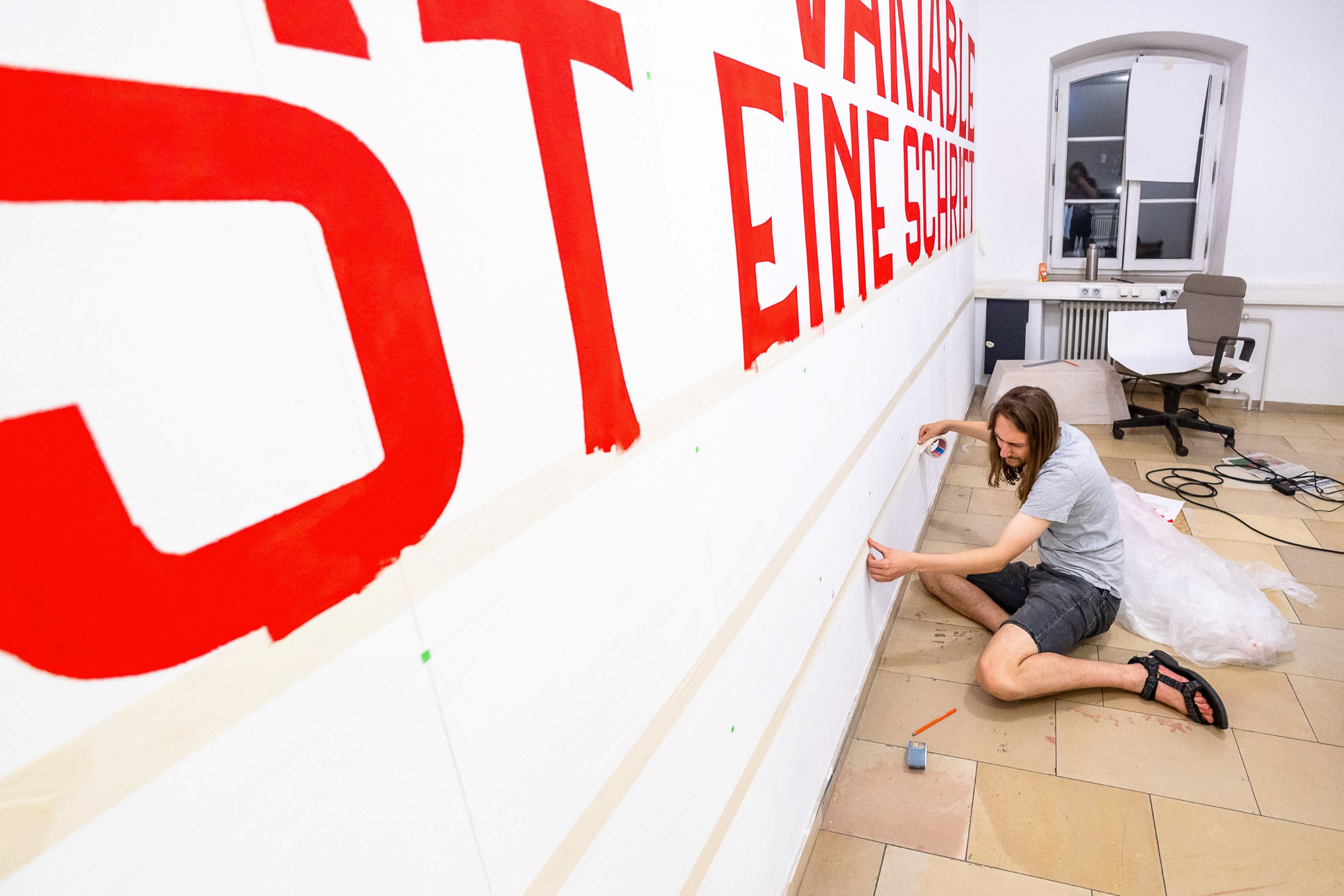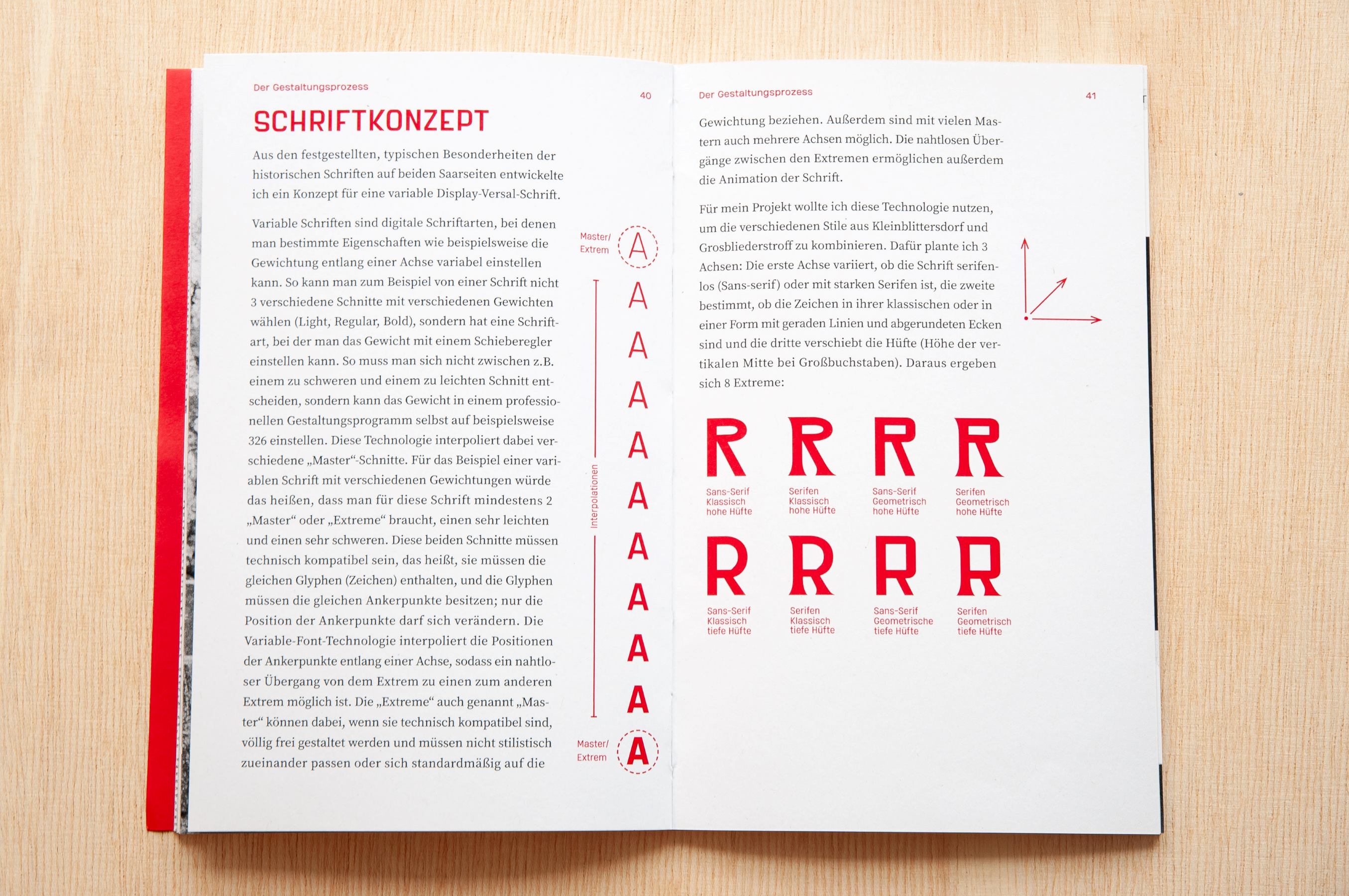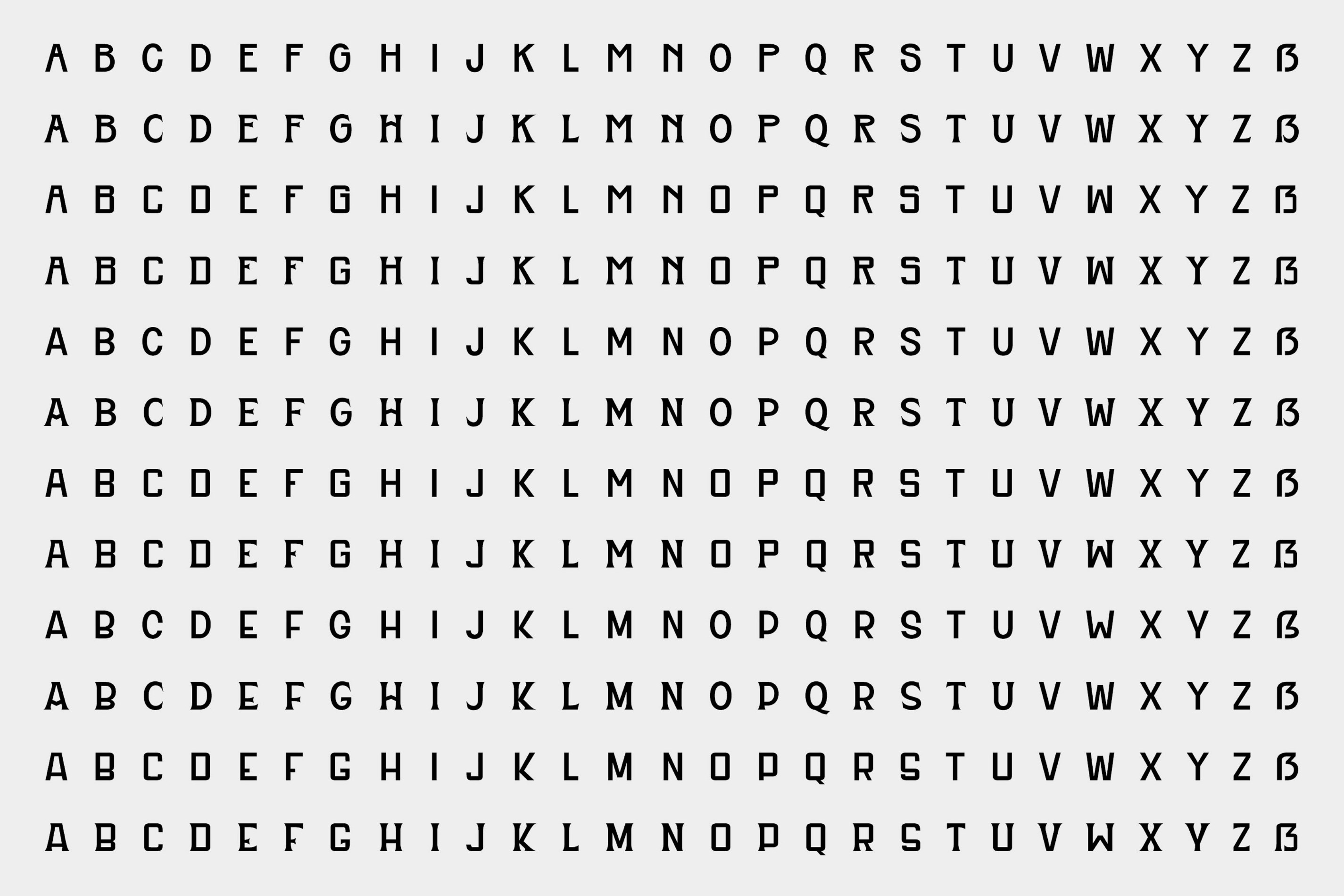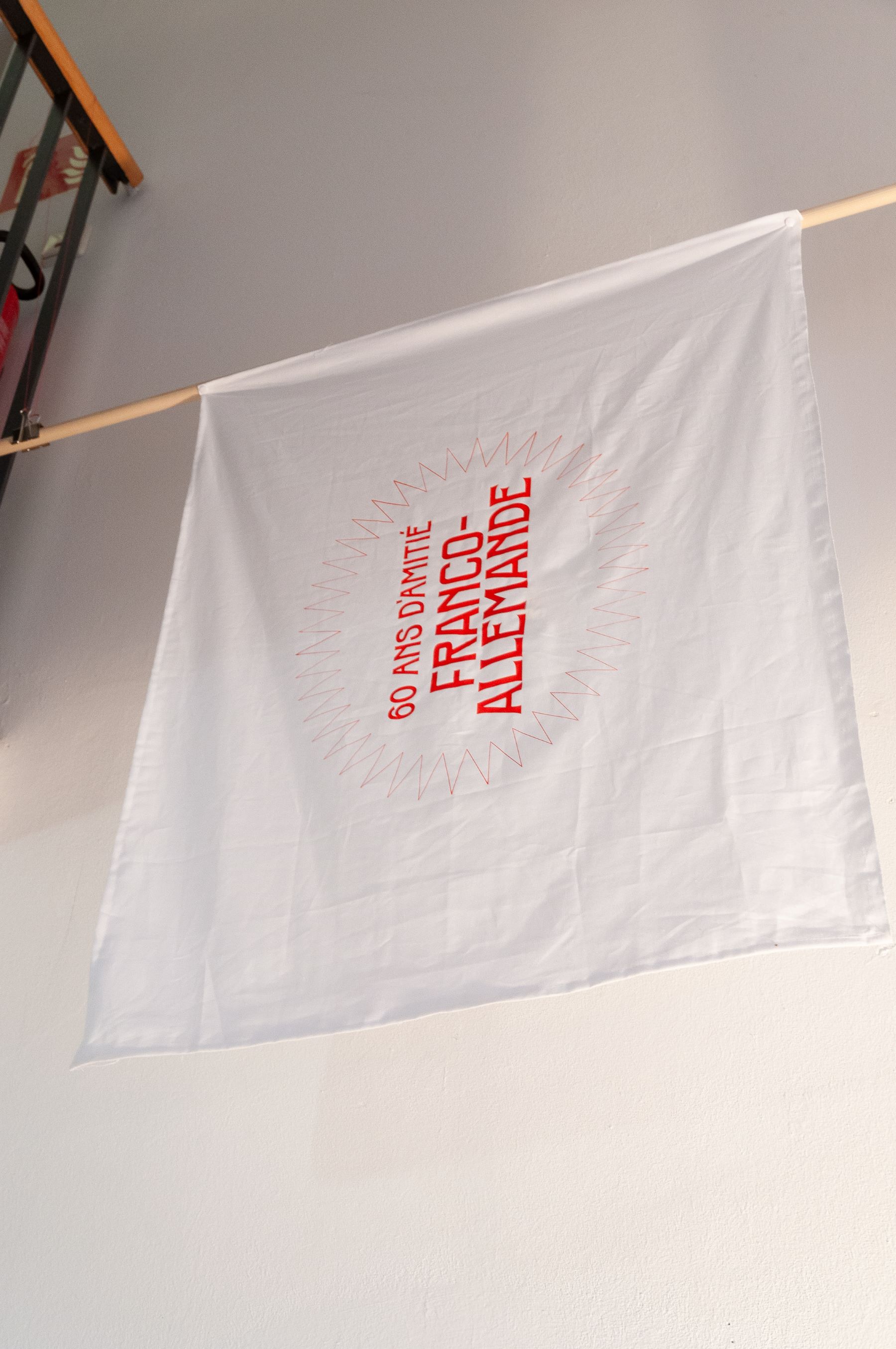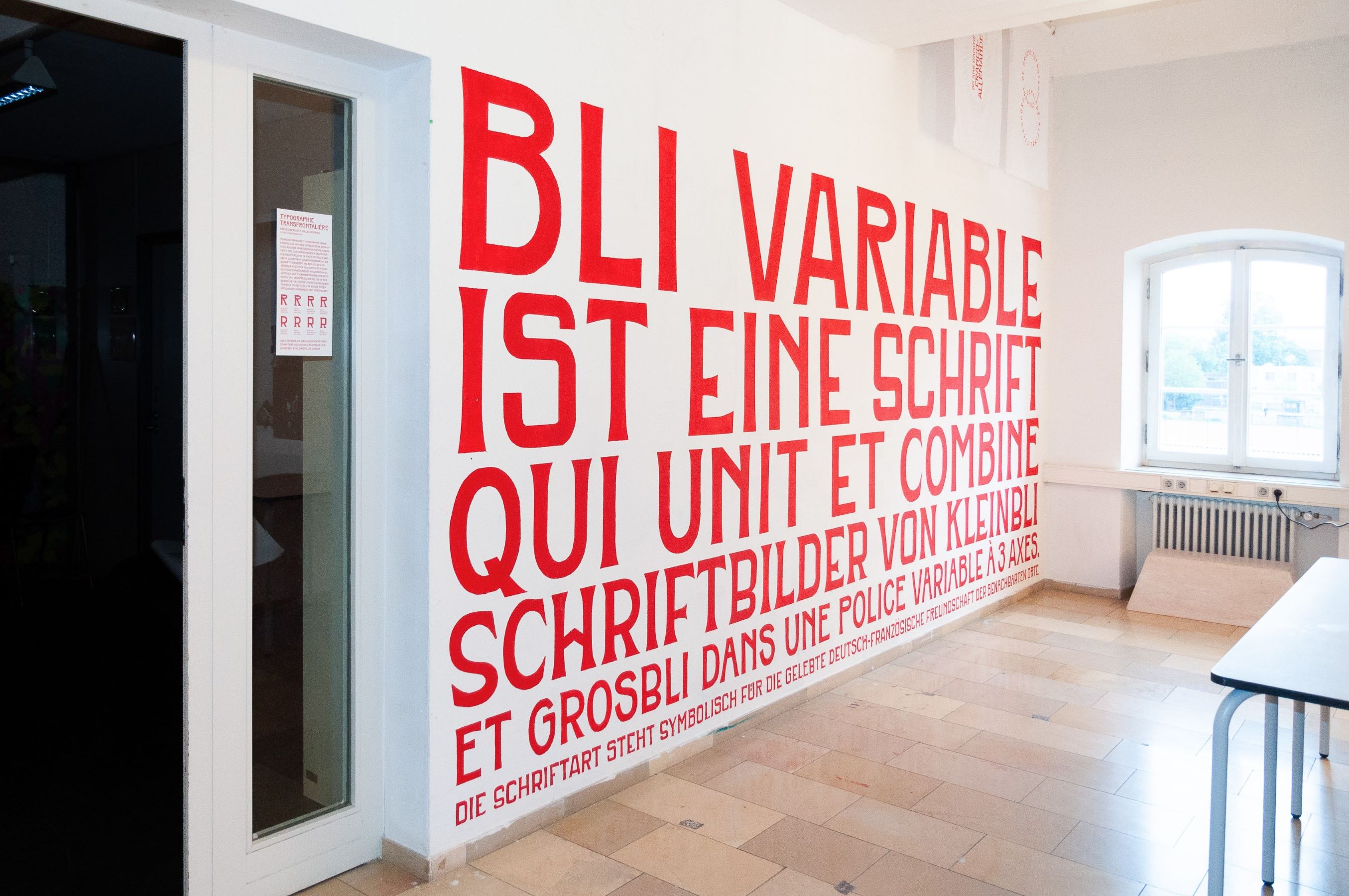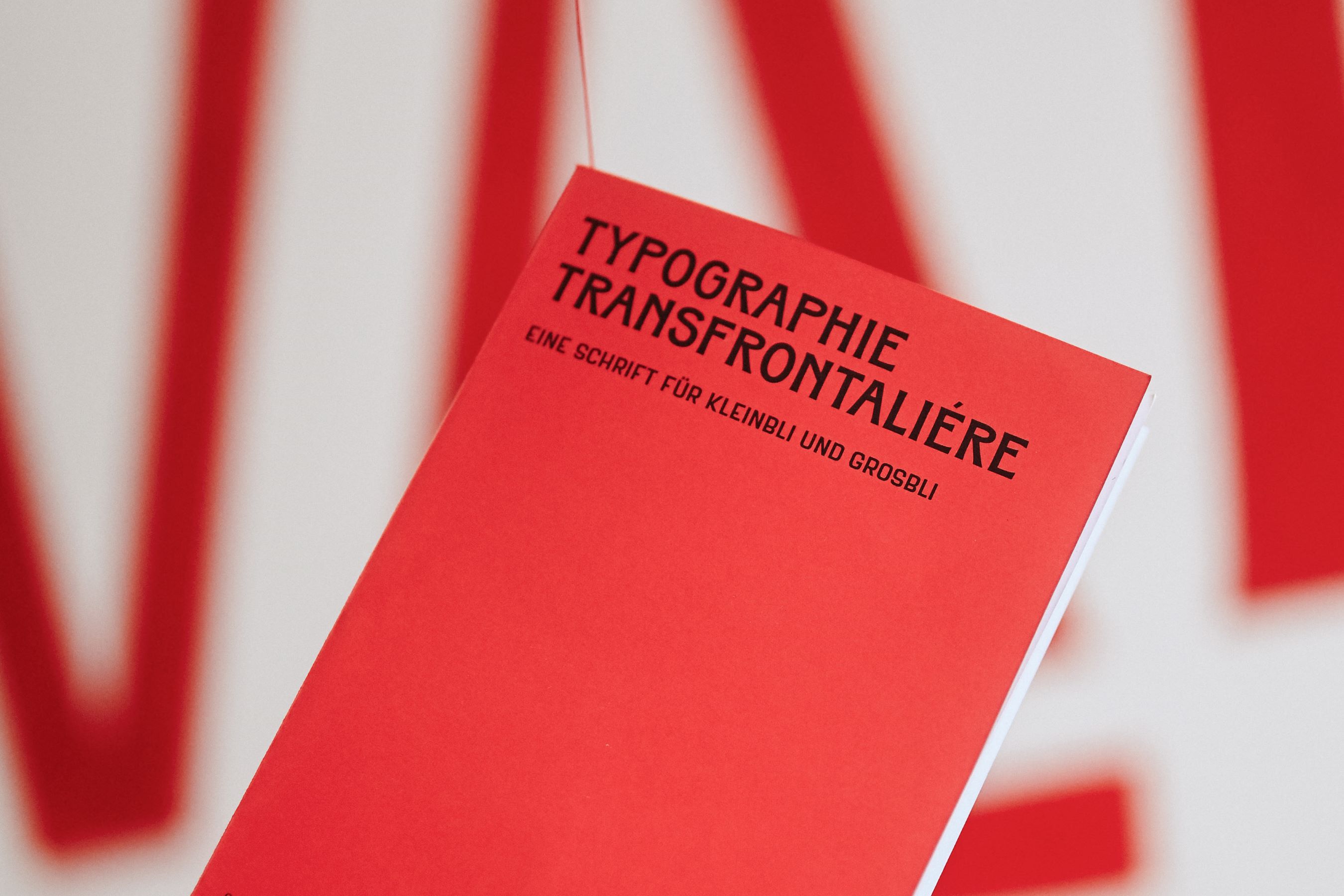
Typographie Transfrontalière: Eine Schrift für Kleinbli und Großbli
Niklas Reiprich: Typographie Transfrontalière: Eine Schrift für Kleinbli und Großbli, Bachelor Kommunikationsdesign, 2023, Ausschnitt Schriftprobenwand, Foto: Vivianne HellNiklas Reiprich: Typographie Transfrontalière: Eine Schrift für Kleinbli und Großbli, Bachelor Kommunikationsdesign, 2023, Ausschnitt Schriftprobenwand, Foto: Vivianne Hell
Im Projekt "Typographie Transfrontalière wurde eine Schriftart entwickelt, die charakteristische Schriftbilder von Kleinblittersdorf in Deutschland und dem benachbarten französischen Grosbliederstroff miteinander verknüpft.
Dieses Vorhaben baut auf einem Hochschulprojekt von 1991 auf, das theoretisch vom Soziologen und Gründungsmitglied der Hochschule Lucius Burckhardt begleitet wurde. Damals hatte man sich zum Ziel gesetzt, saarländischen Orten wie Kleinblittersdorf durch die Betonung ihrer individuellen Besonderheiten eine stärkere regionale Identität und Heimatlichkeit zu verleihen. Diese Methode fand im Rahmen von Typographie Transfrontalière erneut Anwendung.
Kleinblittersdorf und Grosbliederstroff zeichnet ihre grenzüberschreitende Verbundenheit aus, die in der historischen Entwicklung der Orte begründet ist und im öffentlichen Leben beider Gemeinden spürbar wird. Die Verschmelzung der deutsch-saarländischen und französisch-lothringischen Kultureinflüsse wurde im Projekt in eine Schriftgestaltung überführt. Hierzu wurden Schriftbilder auf Schildern, Denkmälern und Gräbern beider Orte untersucht, um charakteristische regionale Besonderheiten herauszuarbeiten. Diese Eigenheiten wurden dann in der Gestaltung einer anpassbaren variablen Schriftart zusammengeführt. Variable Schriftarten ermöglichen eine stufenlose Anpassung ästhetischer Merkmale (wie z.B. Schriftbreite) entlang definierter Achsen.
Die entstandene Schriftart, genannt Bli, erlaubt somit eine flexible Anpassung von Serifen, Ecken und Buchstabenhöhen. Das Ergebnis ist eine subjektive Interpretation und Hervorhebung der typografischen Eigenheiten von Kleinblittersdorf und Grosbliederstroff. Die Schrift vereint die untersuchten Schriftbilder in einem neuen, ausdrucksvollen Schriftbild, das sich harmonisch in die Umgebung beider Orte einfügt und ihre besondere Verbindung betont. Sie zelebriert 50 Jahre nach Unterzeichnung des Élysée-Vertrags die deutsch-französische Freundschaft und Identität in beiden Orten.